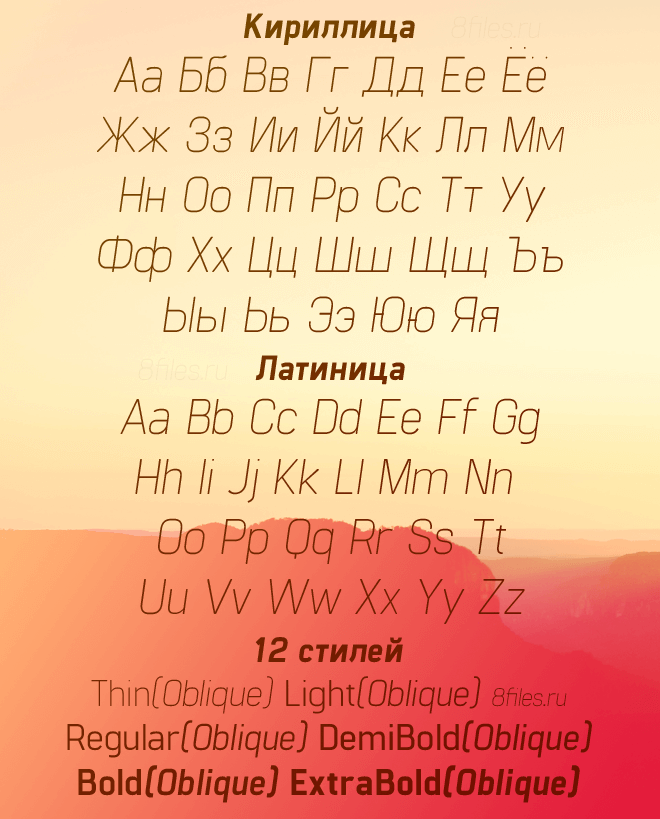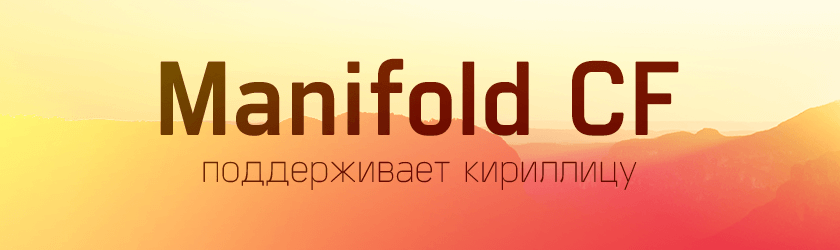
Font (шрифт) Manifold CF
Представляю вашему вниманию приятный и современный шрифт (font) Manifold CF. Шрифт имеет 12 стилей и поддержку Кириллицы. Скачай Manifold CF и используй в личных нуждах